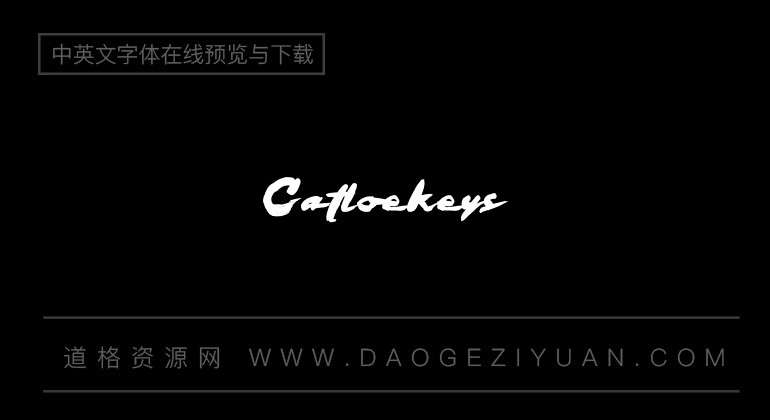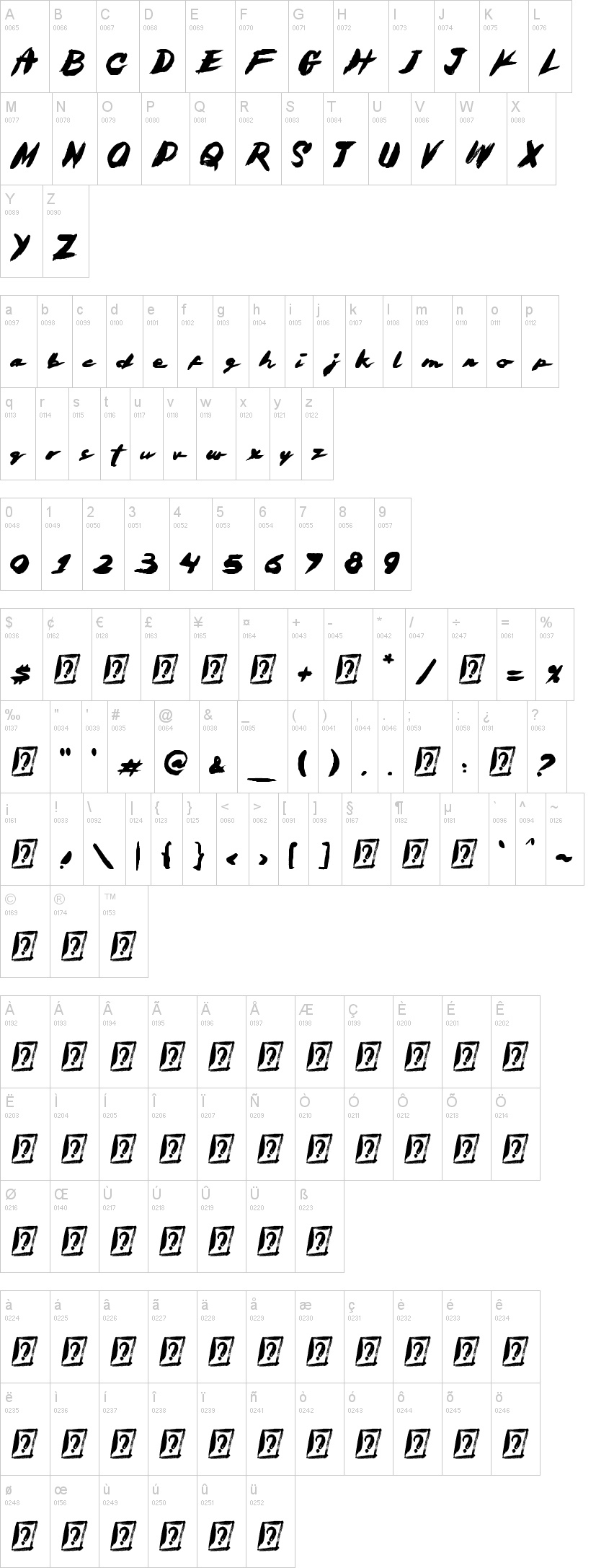
Catloekeys 是一种手写字体,它采用了流畅的笔画和类似于日记本上手写字的风格。这种字体看起来非常自然和舒适,同时给人一种个人化的感觉。Catloekeys 字体适合用于手写信件、日记、卡片等场合,可以帮助用户传达一种亲密和温馨的感觉。此外,Catloekeys 字体也适合用于设计海报、广告等场合,可以给人一种新鲜和有趣的感觉。总之,Catloekeys 字体是一种非常独特和多用途的字体,非常适合那些想要表达自己独特个性的用户。内容介绍
Catloekeys是一款非常不错的手写艺术字体,具有很好的视觉感,适合于文化类的宣传设计、商业类品牌的广告和产品包装设计以及个性化文字排版等较多场景。